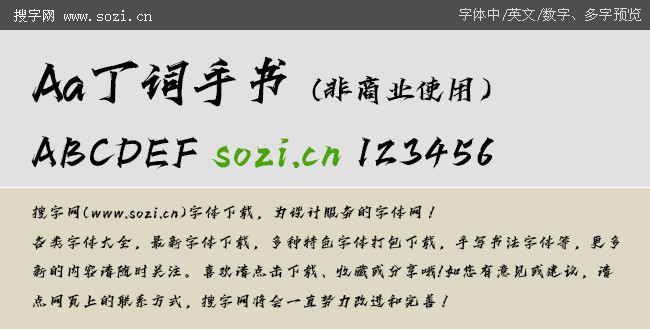
Aa丁詞手書(shū)
搜字網(wǎng)給大家提供一款A(yù)a丁詞手書(shū)(非商業(yè)使用)字體下載,該字體是一款手寫(xiě)風(fēng)格字體,這款字體比較個(gè)性,字跡顯得連貫干練而不凌亂,字形凌厲大方,具有很好的視覺(jué)感。適合書(shū)裝設(shè)計(jì)、包裝設(shè)計(jì)、海報(bào)設(shè)計(jì)等應(yīng)用(此字體為個(gè)人非商用版,商用可以聯(lián)系QQ:1006760504)。